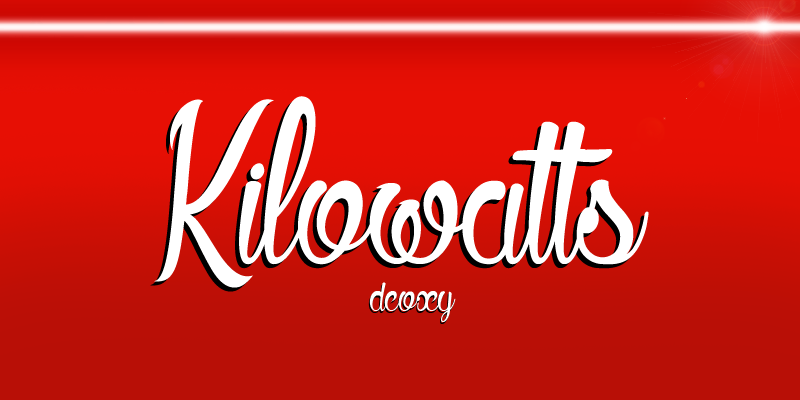
Kilowatts Font é uma elegante escolha para designers buscando um estilo autêntico e suave na sua próxima criação visual. Criada pelo designer Hamilton, esta fonte está disponível como cópia de mão escrita que transmite tranquilidade e confiabilidade com cada traço perfeito. Com uma linguagem fluida e um design natural, Kilowatts é ideal para qualquer projeto que valoriza o cuidado no detalhe. Com sua aparência minimalista mas envolvente, esta fonte oferece a quem usa-a a oportunidade de criar mensagens sólidas em seu trabalho sem perder a personalização devido ao estilo autêntico da mão escrita. Para qualquer projeto que exija uma fonte autêntica e elegante, Kilowatts é um excelente escolha. Se estiver procurando por uma fonte suave com um toque de originalidade, então você provavelmente encontrará tudo isso nesta fonte criada pelo designer Hamilton. Por favor, entre em contato antes para obter seu próprio license.